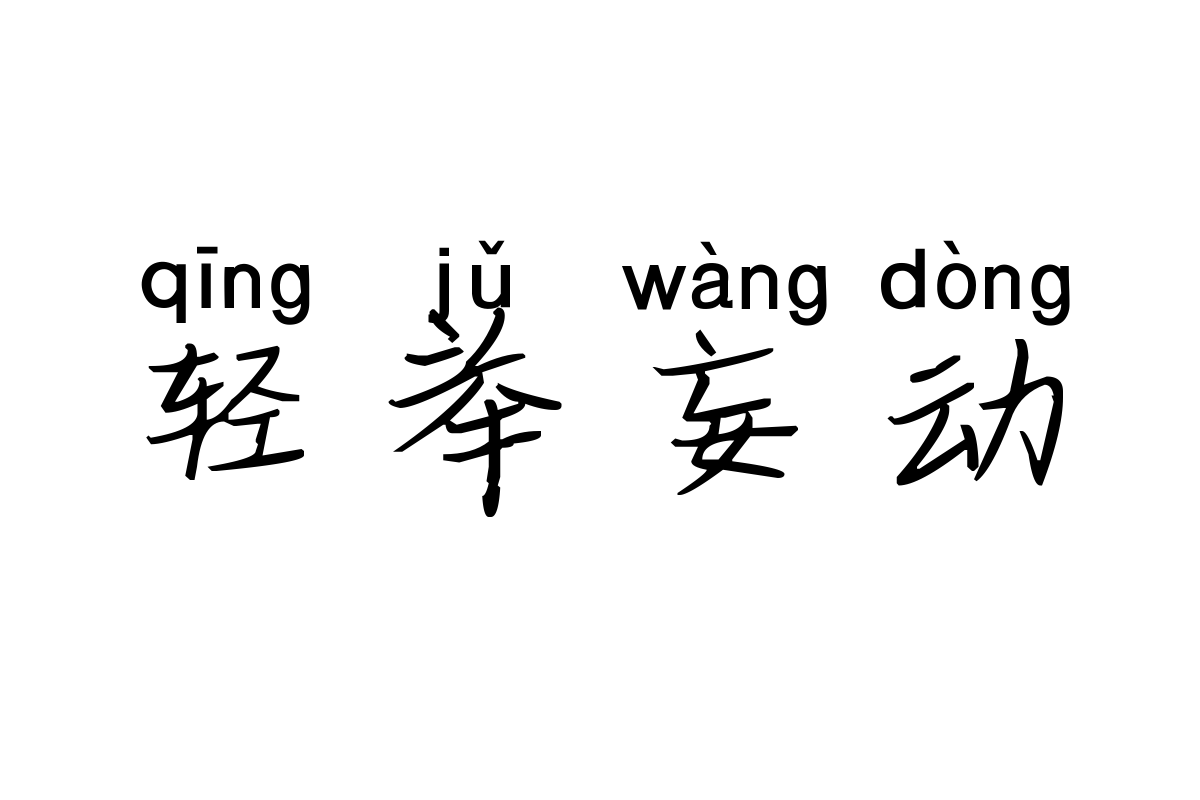
米开爱(Mi Kai Ai)是一种艺术字体,由设计师米开爱创作。这种字体以其独特的设计和视觉效果而闻名,被广泛应用于各种设计项目中。
米开爱字体的特点是其简洁的线条和流畅的曲线,使得文字看起来既美观又易读。这种字体适合用于标题、正文、广告等场合,能够很好地传达信息并吸引观众的注意力。
此外,米开爱字体还具有一定的可扩展性,可以与其他字体组合使用,创造出更多创意的设计效果。这使得它成为了设计师们非常喜欢的字体之一。